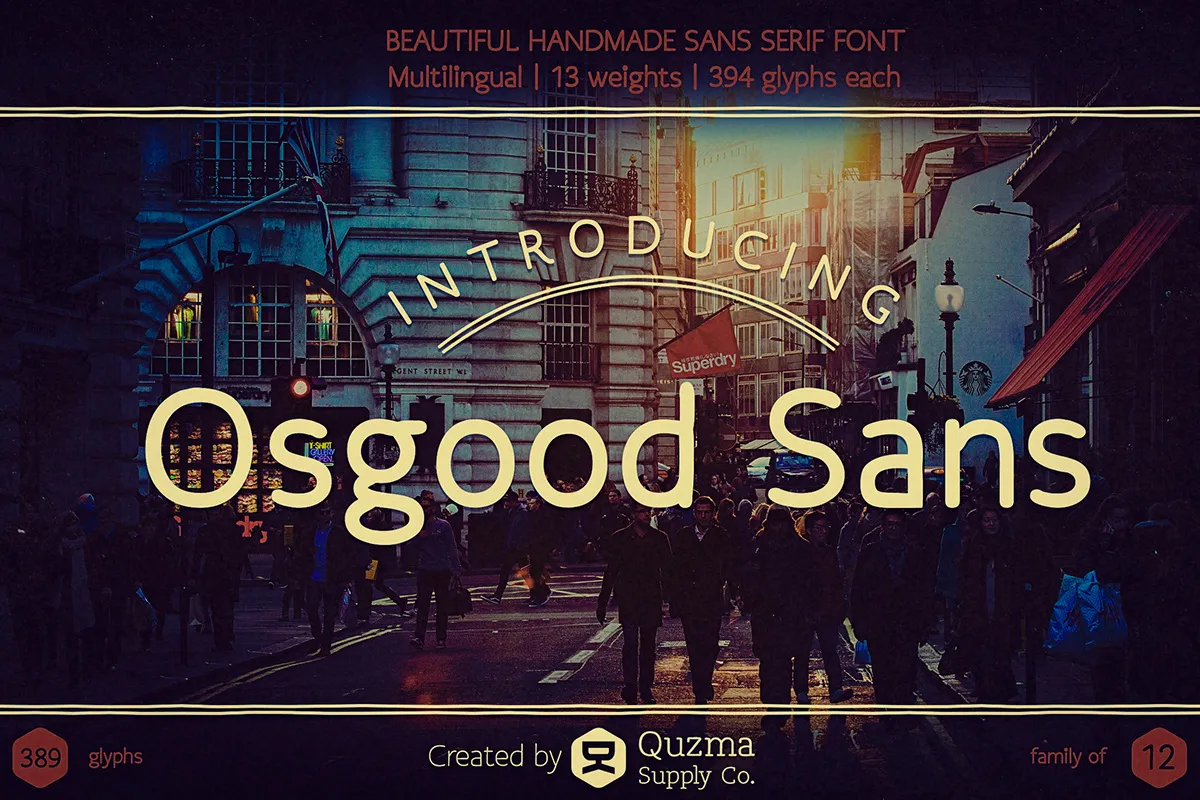
A Osgood Sans é uma elegante fonte sans-serif que foi projetada com carinho para se adaptar perfeitamente a diversas aplicações. Essa fonte amigável e confortável, ideal tanto para textos extensos quanto para os pequenos detalhes de sinalização ou arte vintage, funciona maravilhosamente em qualquer tamanho. Sua simplicidade e beleza fazem dela uma escolha ótima para qualquer projeto que valorize a legibilidade e o estilo moderno. Ideal tanto para escrita formal quanto informal, Osgood Sans é perfeita para criar um visual elegante sem perder a versatilidade necessária em design de interface de usuário ou branding. Seja você um designer gráfico experiente ou um iniciante que busca uma fonte para seu próximo projeto, Osgood Sans tem algo especial para oferecer.